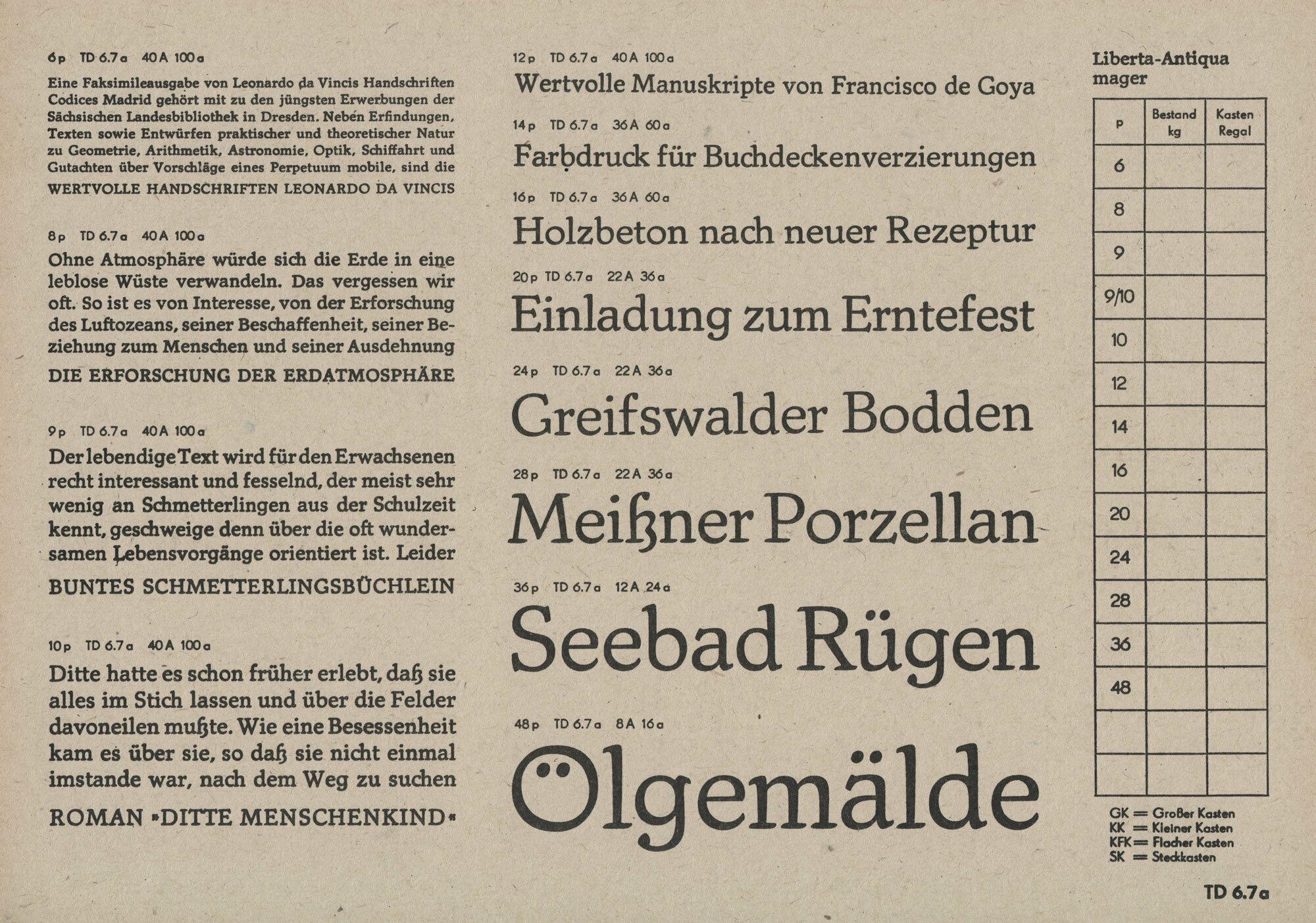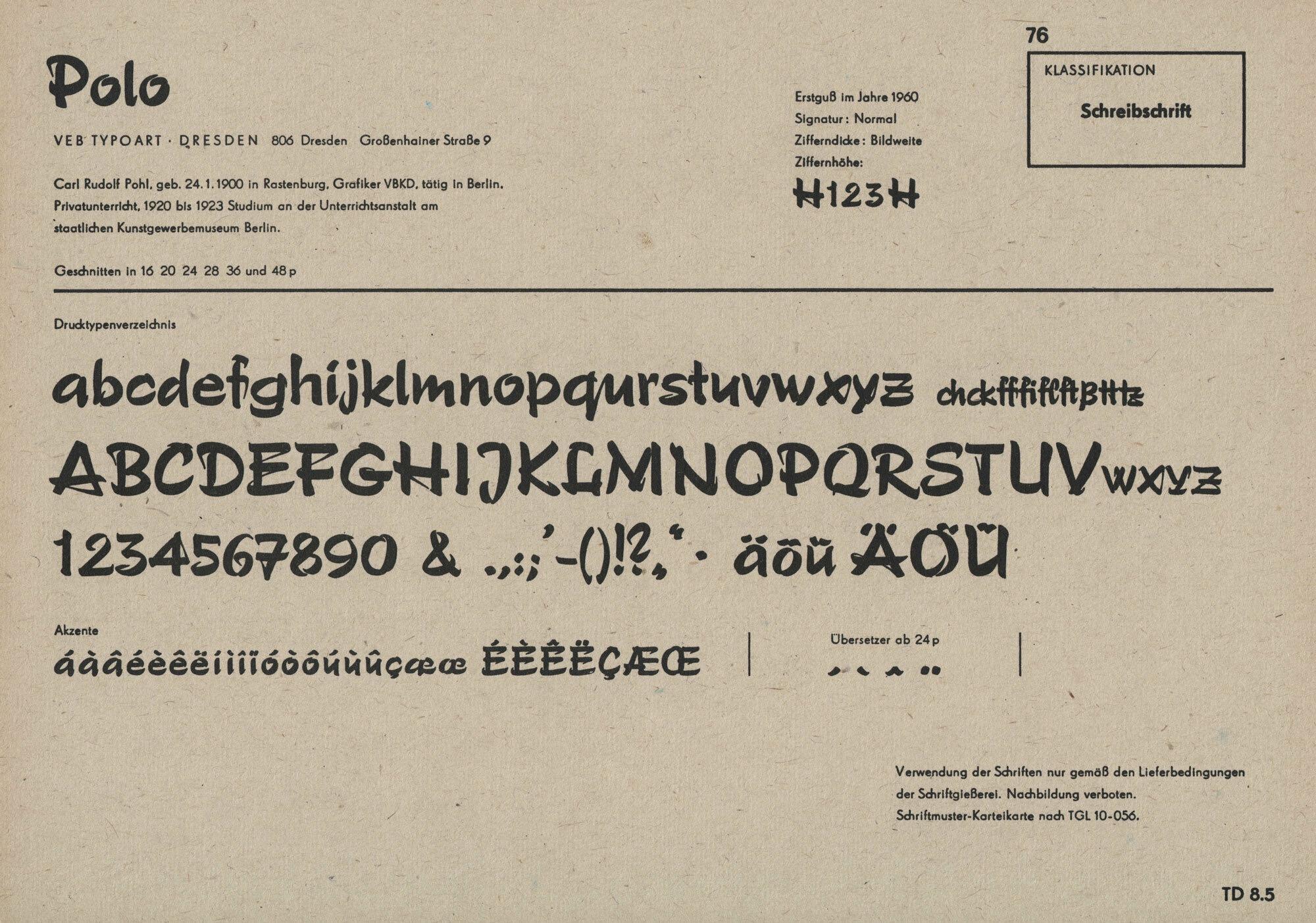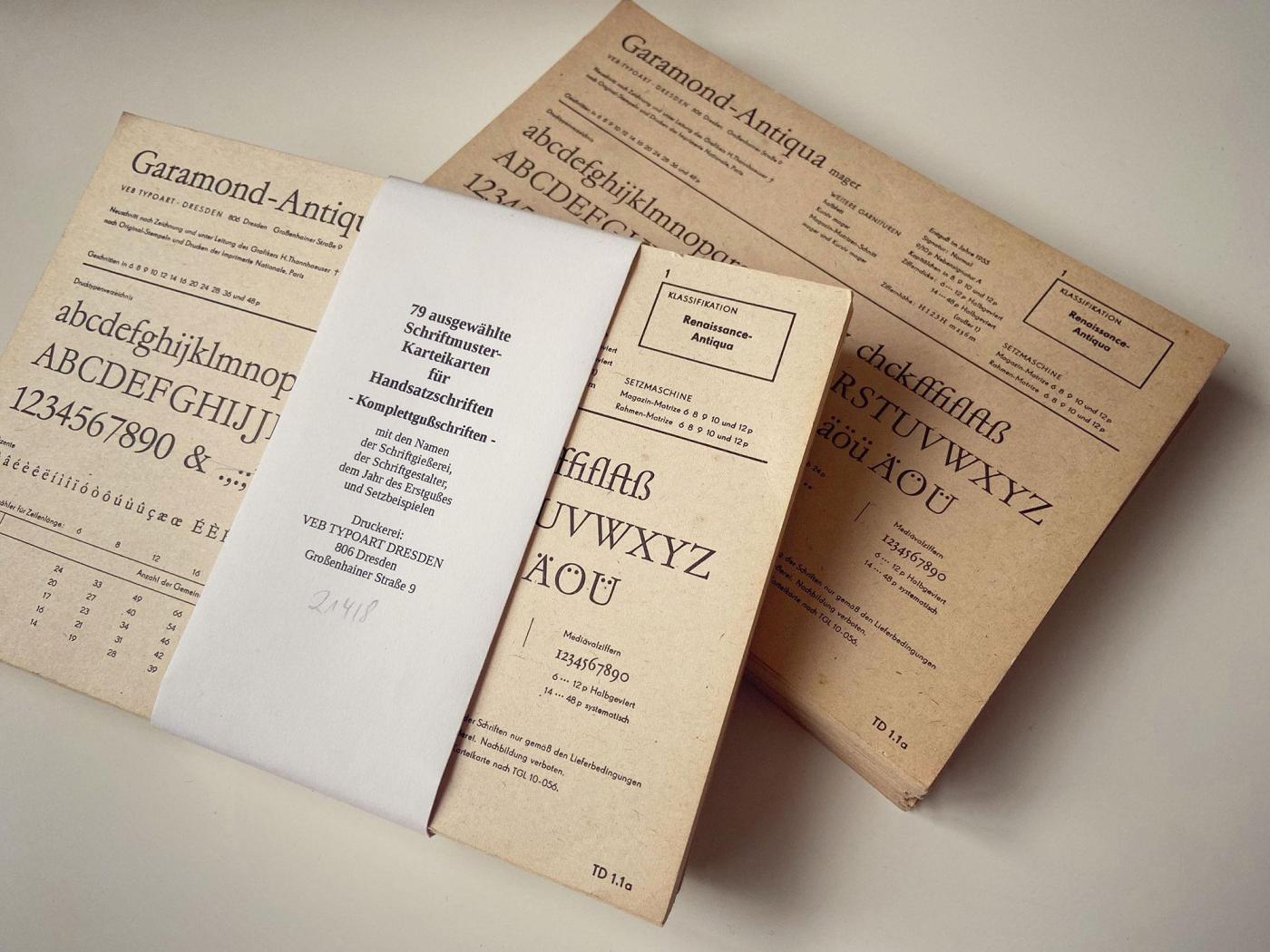
Parallel zu den Schriftmustern westdeutscher Bleisatzschriften als Karteikarten gab es auch in der DDR entsprechende Drucke. Als alleiniger verbliebener Hersteller auf dem Staatsgebiet gehören alle Schriften zum VEB Typoart Dresden. Das Aussehen der A5-großen Karteikarten war normiert nach TGL 10-056 (später ersetzt durch TGL 24 473) und stand in Verbindung mit der Schriftklassifikationsnorm TGL 10-020.
Entsprechend der Normen enthielten die Karten:
- Angaben zu Schriftname, Schriftstil, Schnitt und weiteren Garnituren innerhalb der Schriftfamilie
- Angaben zum Gestalter und zum Erstguss
- erhältliche Schriftgrade
- technische und gestalterische Details (Signatur, Zifferndicke und -höhe, Zeilenlängen für Fließtextschriften etc.)
- Abbildung Figurenverzeichnis einschließlich Akzente, Übersetzer, Ligaturen und Sonderzeichen
- Satzbeispiele auf der Rückseite
Durch die Normierung existiert für jeden Schriftschnitt eine eindeutige Identifikations- bzw. Bestellnummer nach dem Prinzip Schriftklassifikationsnummer + Laufende Nummer als Identifikation der Schriftfamilie + Variante bzw. Schriftschnitt als Kleinbuchstabe (falls zutreffend)
Beispiele: »1.1a« für »Garamond-Antiqua mager« oder »6.3« für »Erler-Versalien« ohne Varianten.
1. Renaissance-Antiqua
- 1.1 Garamond-Antiqua
- 1.2 Minister-Antiqua
- 1.3 Tschörtner-Antiqua
- 1.4 Roesner-Versalien
2. Barock-Antiqua
- 2.1 Fleischmann-Antiqua
3. Klassizistische Antiqua
- 3.1 Bodoni-Antiqua
- 3.2 Didot-Antiqua
- 3.3 Pergamon-Antiqua
- 3.4 Marko
4. Serifenbetonte Linear-Antiqua
- 4.1 Technotyp
- 4.2 Schreibmaschinenschrift
5. Serifenlose Linear-Antiqua
- 5.1 Koralle-Grotesk-Versalien
- 5.2 Mimosa
- 5.3 Super-Grotesk
- 5.4 DIN-Norm-Spiegelschrift
- 5.5 Grotesk-Versalien
- 5.6 Fundamental-Grotesk
6. Individuell betonte Schriften
- 6.1 Thannhaeuser-Schrift
- 6.2 Meister-Antiqua
- 6.3 Erler-Versalien
- 6.4 Thomas-Schrift
- 6.5 Sinkwitz-Versalien
- 6.6 Agitator
- 6.7 Liberta
7. Sachlich betonte Schriften
- 7.1 Primus-Antiqua
- 7.2 Manutius-Antiqua
- 7.3 Magna
8. Schreibschriften
- 8.1 Splendor
- 8.2 Impuls
- 8.3 Kurier
- 8.4 Lotto
- 8.5 Polo
- 8.6 Arabella-Favorit
- 8.7 Stentor
9. Gebrochene Schriften
- 9.1 Sinkwitz-Gotisch
benutzte Schriftschnitt-Identifikationen (nur Handsatz):
- a – mager
- b – buch
- c – halbfett
- d – dreiviertelfett
- e – fett
- f – extrafett
- g – schmalmager
- h – schmalhalbfett
- i – schmalfett
- j – kursiv
- k – kursiv halbfett
- l – kursiv fett
- r – breitmager
- s – breithalbfett
- t – breitfett
Die Karten erschienen zunächst ohne Nummerierung und enthielten auch Karten nur für Setzmaschinenschriften. Spätere, nummerierte Nachdrucke zeigen nur noch eine Auswahl, um »die Ausbildung des Facharbeiters für Satztechnik anschaulich zu unterstützen«.